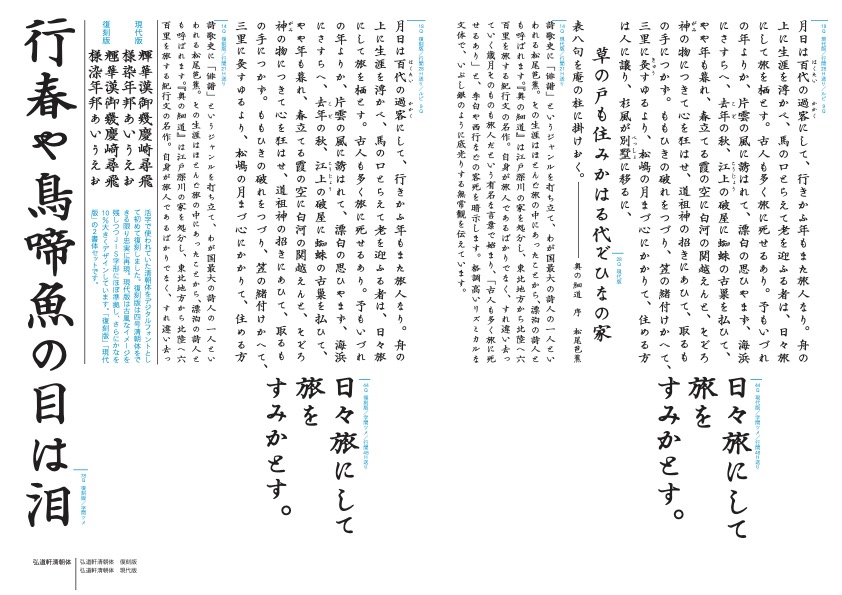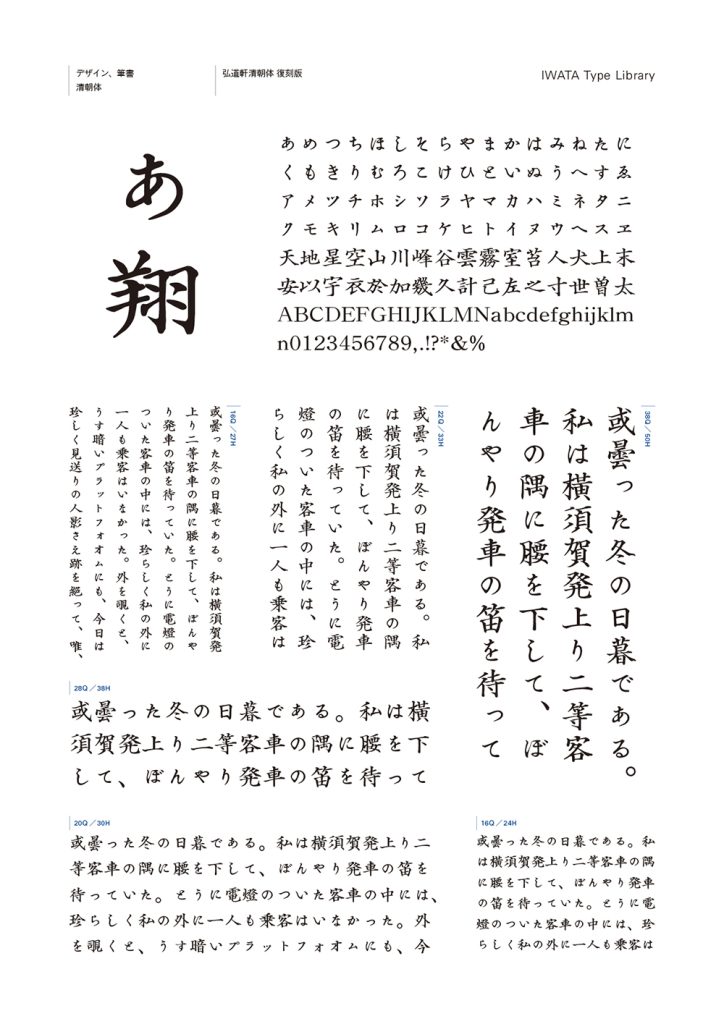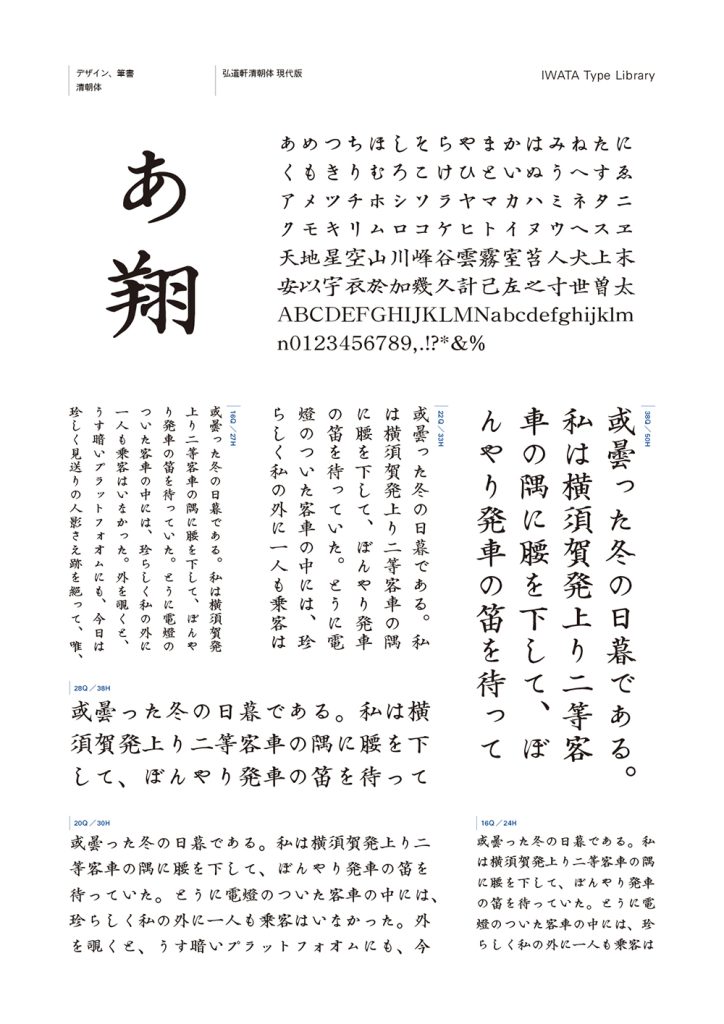
日本最古の部類に入る金属活字楷書体「弘道軒清朝体」をデジタルフォントとして復刻した筆書系書体です。
四号清朝体を基本に鋼鉄の角棒に手で直接彫り込む伝統的な手法で作られた活字の鋭角的なシルエットを継承しつつ、デジタルフォントとしての使いやすさを備えています。
活字を忠実に再現した「復刻版」と、古風な印象を残しながらもJIS字形に準拠した「現代版」の二種類があります。
案内状、俳句、歌集など、格式のある文章や和の趣を大切にしたデザインに適した、品格と風格を兼ね備えた書体です。